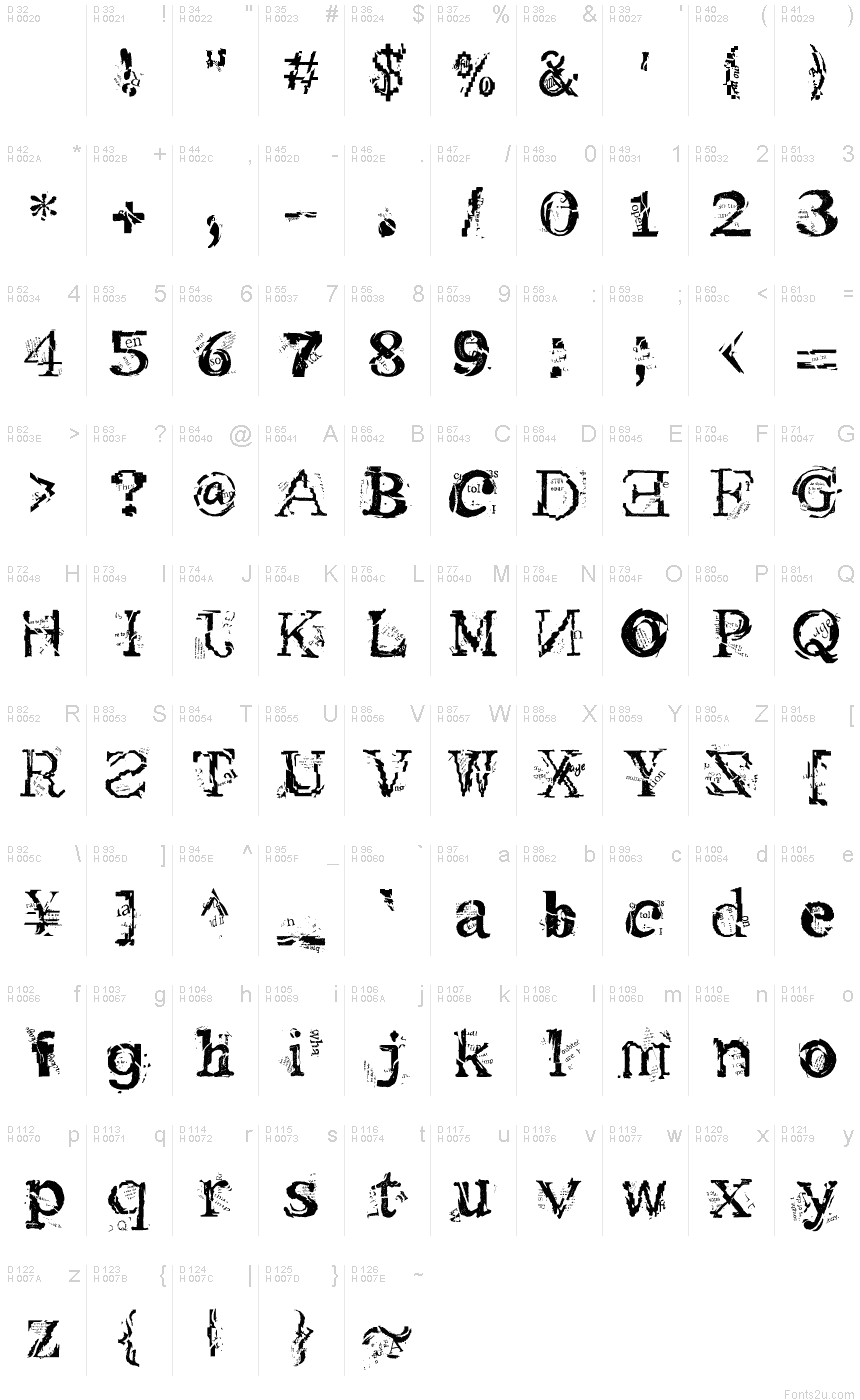
Metacopy Plain od Yoshiki create to darmowy, zniekształcony krój typu display o fakturze podartej kserokopii i poszarpanych krawędziach, dzięki którym litery wyglądają na zdrapane i łatane. Szorstka powierzchnia jest spójna we wszystkich znakach, co sprawia, że liternictwo wygląda jak wycięte ze zniszczonego wydruku, a nie jak czysty, cyfrowy projekt.
Metacopy Plain wnosi klimat „cut-and-paste” na okładki zinów, ulotki koncertowe, okładki albumów, grafikę protestacyjną i wielkoformatowe nagłówki redakcyjne. Sprawdzi się też w kolażach i na stemplowanych etykietach, gdzie bardziej od gładkiego wykończenia liczy się ręcznie wykonany, „zabrudzony” tuszem charakter.